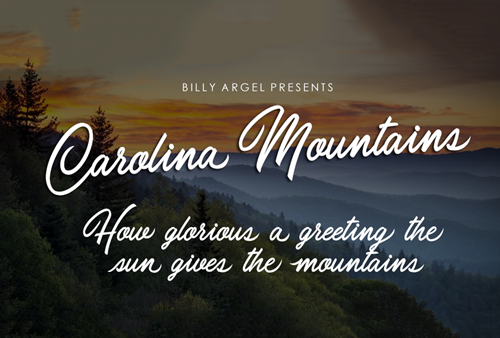
Carolina Mountains Font – Download Grátis
A Carolina Mountains Font é uma opção única para designer que buscam personalidade e elegância no seu trabalho, oferecendo linhas fluidas e aconchegantes. Desenvolvida pelo talentoso Billy Argel, esta fonte Script se destaca por sua disposição versátil em variados estilos, desde escrita casual até uma aparentemente natural utilização de letras grandes. O design da Carolina Mountains Font é parte do conjunto completo e está disponível para quem desejar usar a fonte comercialmente. A fonte também pode ser usada de forma pessoal sem custos adicionais, com licença comercial disponível apenas através de seu site oficial. Se você se interessou por mais detalhes ou solicitações de desenvolvimento de novas fontes, Billy Argel está atento para fornecer assistência através do e-mail  Não perca a oportunidade de experimentar essa fonte incrivelmente personalizável; visite seu site oficial ao clicar no link à sua disposição.